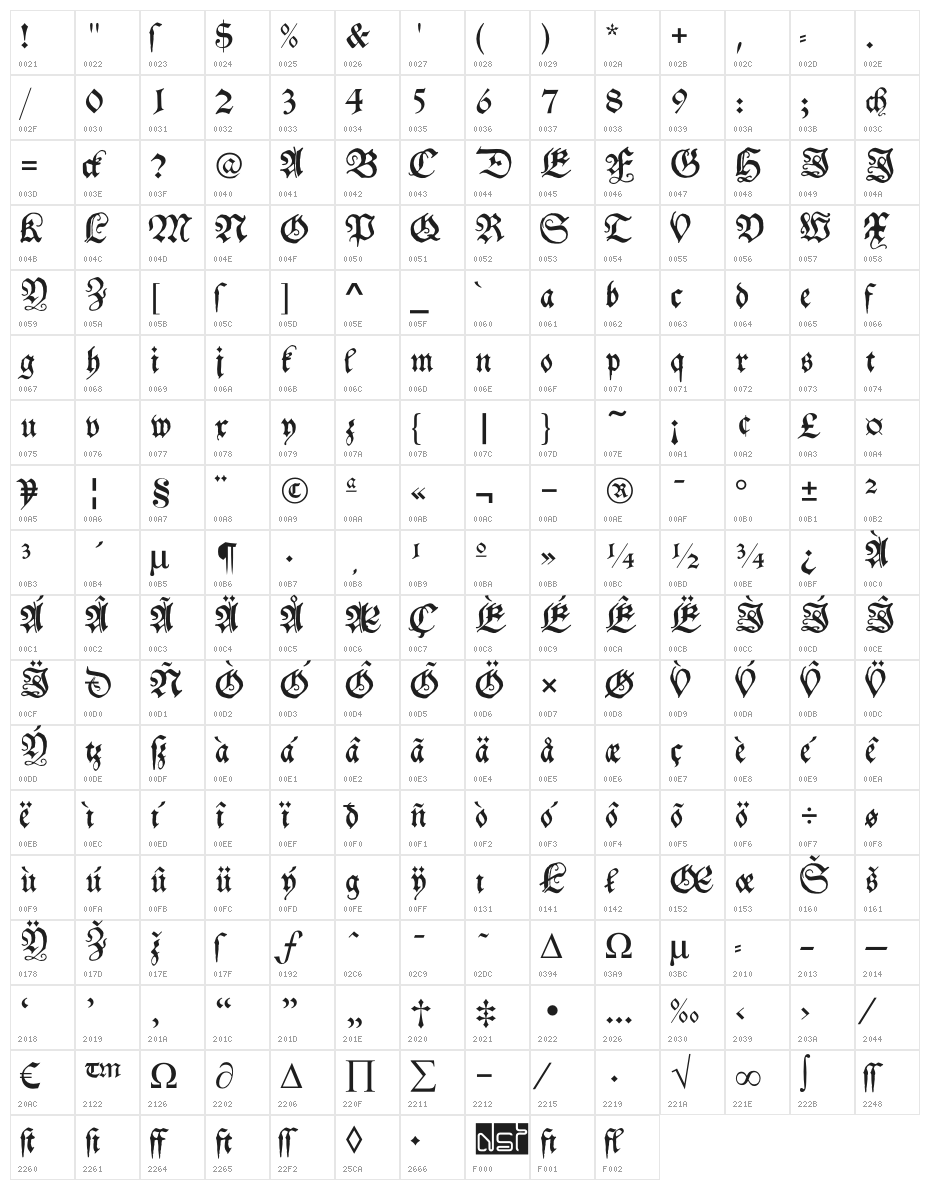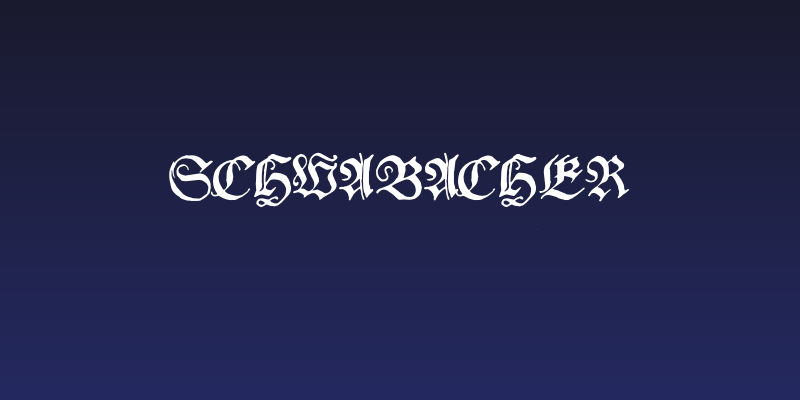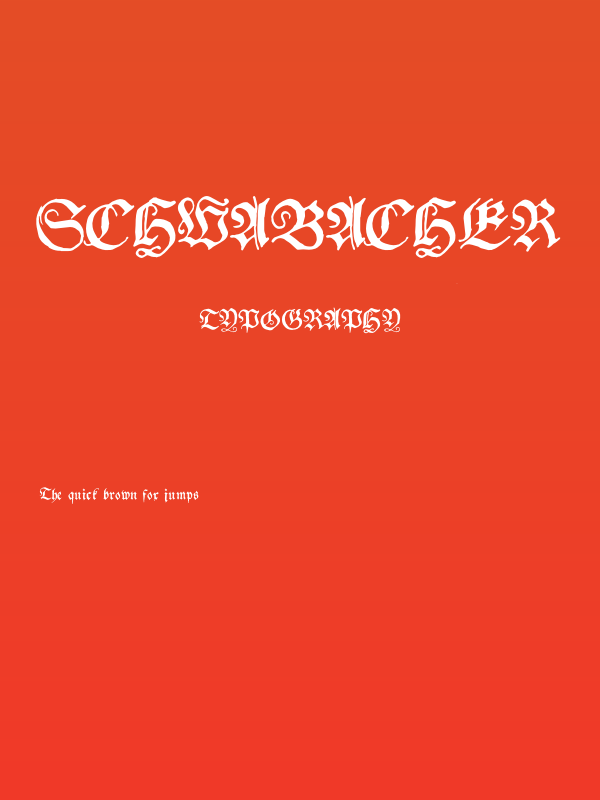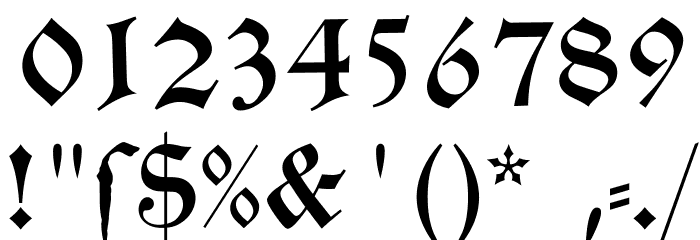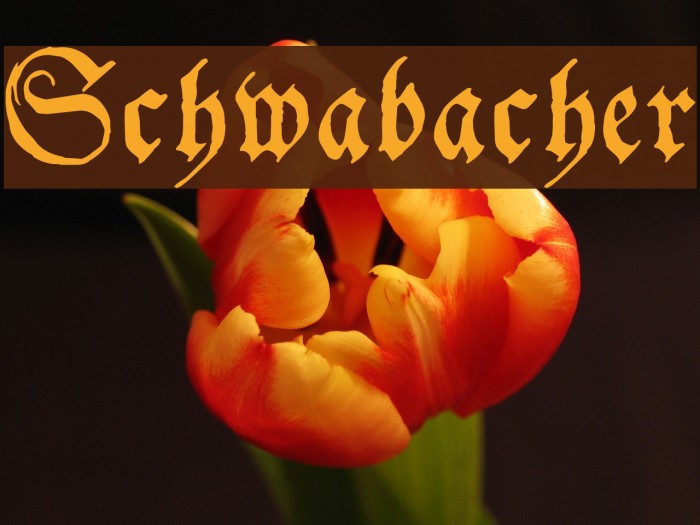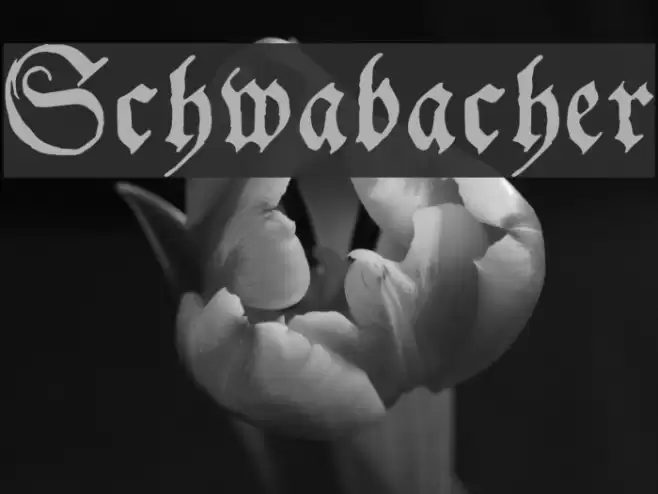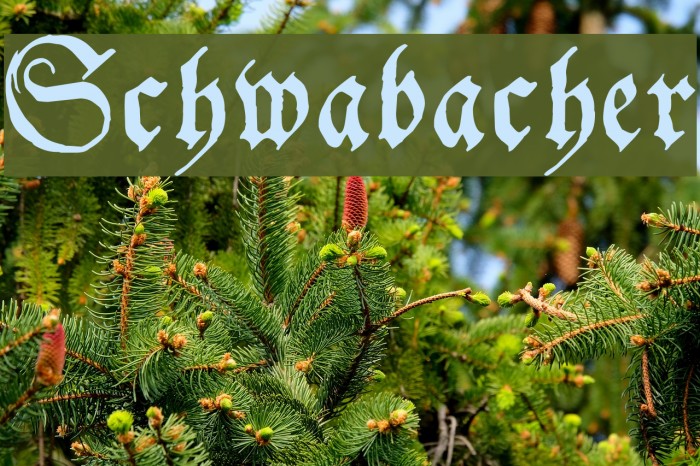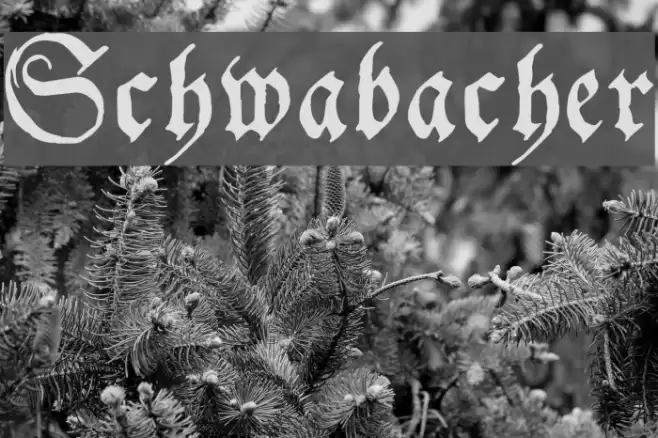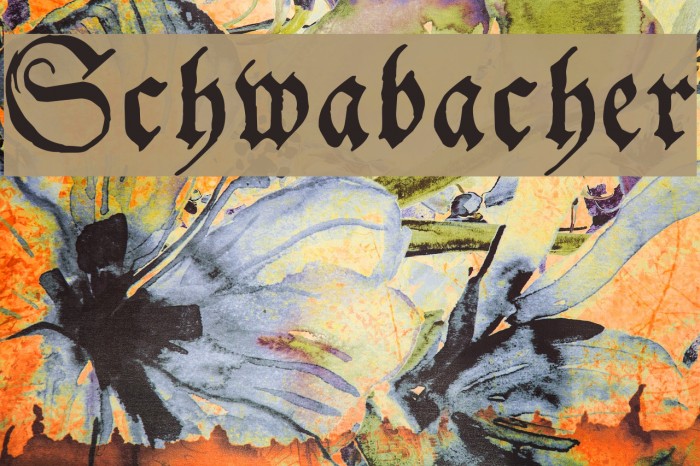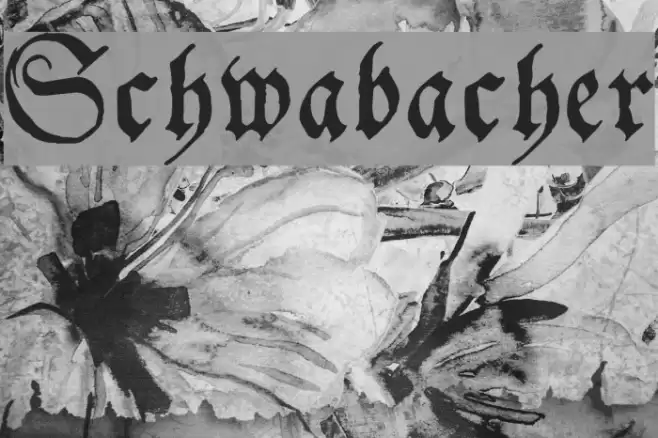
Schwabacher Font
Fonts by Dieter Steffmann
| Cas d'utilisation | Logos, Headlines, Decorative text |
| Projets proposés | Ideal for projects requiring a historical or medieval touch, such as book covers, posters, or themed event invitations. |